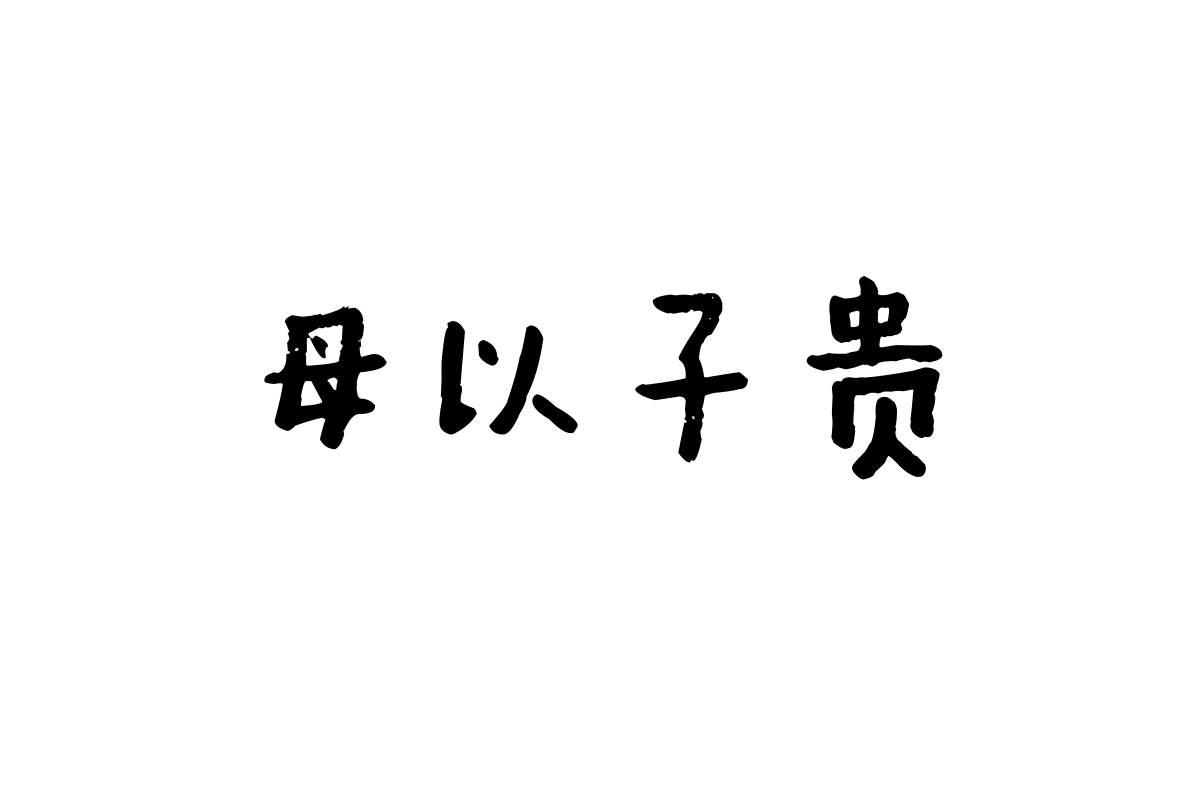
汉仪新蒂蜡笔体是一款专为儿童设计的艺术字体,具有独特的卡通风格和可爱的线条。这款字体笔画圆润、流畅,适合用于儿童书籍、贺卡、海报等创意设计。同时,汉仪新蒂蜡笔体的字形结构紧凑,易于阅读和识别,也适合用于成人的商务和广告设计。
汉仪新蒂蜡笔体的特点:
1. 简洁可爱:汉仪新蒂蜡笔体的字形结构紧凑,线条圆润,给人一种简洁而可爱的视觉感受。
2. 易于识别:由于字形结构紧凑,汉仪新蒂蜡笔体的笔画分布均匀,易于识别,适合用于各类设计作品。
3. 适用范围广:汉仪新蒂蜡笔体不仅适用于儿童书籍、贺卡、海报等创意设计,还适合用于成人的商务和广告设计,具有较强的通用性。